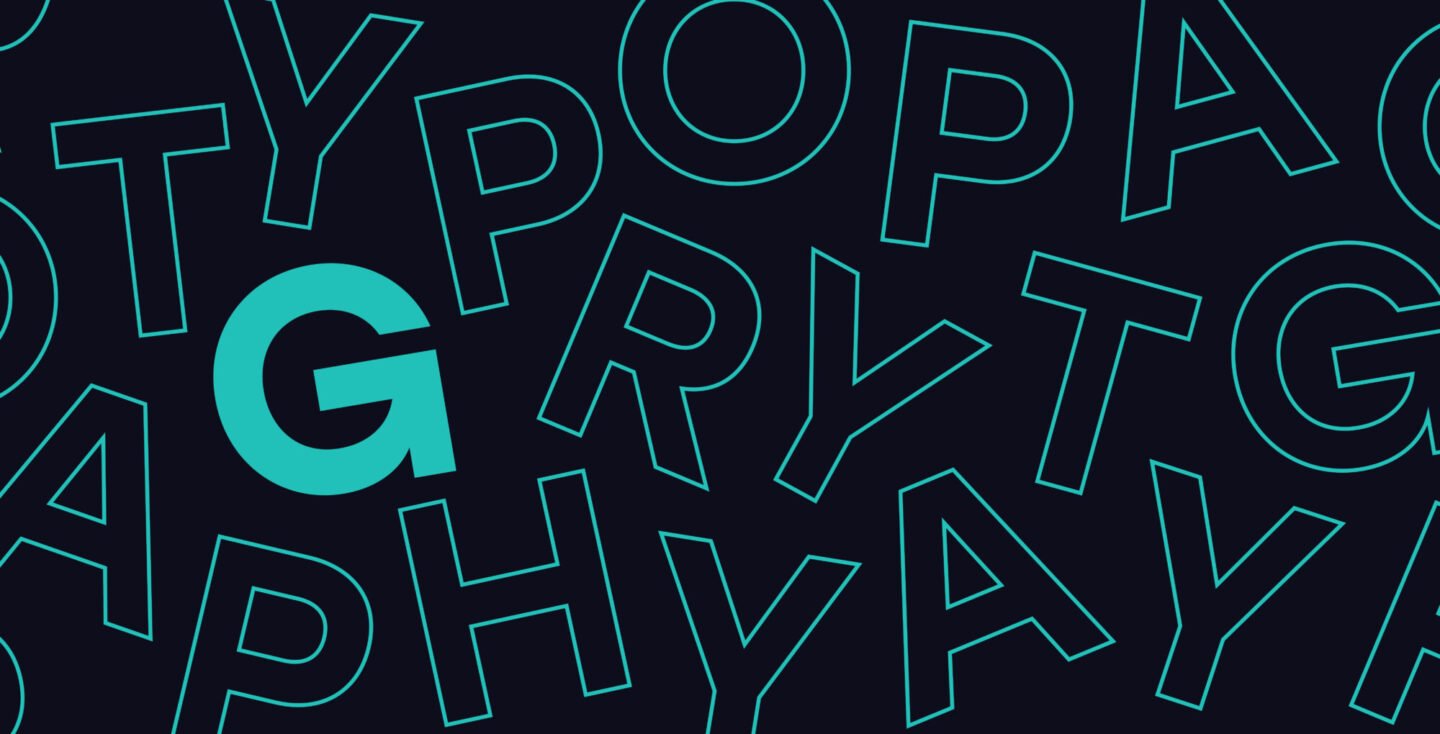
La typographie moderne est l’art de disposer le texte de manière esthétiquement agréable et facile à lire. Dans le passé, la typographie était principalement utilisée pour l’impression de livres et d’autres documents écrits, mais avec l’avènement de la technologie numérique, elle est devenue une partie importante de la conception graphique et de la communication visuelle. Aujourd’hui, le choix d’une police de caractère moderne contribue fortement à l’identité d’un projet visuel.
L’un des principaux principes de la typographie moderne est la hiérarchie. Cela signifie organiser le texte de manière à indiquer clairement l’importance relative de chaque morceau de texte. Par exemple, un titre peut être affiché en police plus grande et plus audacieuse que le texte principal, pour attirer l’attention du lecteur.
Un autre aspect important de la typographie moderne est la lisibilité. Les polices de caractères, ou polices, sont soigneusement choisies pour rendre le texte facile à lire sur différents appareils et à différentes tailles. Par exemple, une police avec une hauteur de x (la distance entre la ligne de base et la ligne moyenne des lettres minuscules) est généralement plus lisible qu’une police avec une faible hauteur de x.
En plus de la hiérarchie et de la lisibilité, la typographie moderne met également l’accent sur le design et l’esthétique. L’utilisation de différentes polices, tailles et styles peut ajouter de l’intérêt visuel à une page et aider à transmettre une humeur ou un ton spécifique. Par exemple, un document officiel peut utiliser une police à empattement, tandis qu’un site Web ludique peut utiliser une police sans empattement plus fantaisiste.
Un des développements les plus intéressants en matière de typographie moderne est l’utilisation de polices personnalisées. Dans le passé, les designers étaient limités à un petit nombre de polices préinstallées, mais maintenant ils peuvent créer leurs propres polices ou utiliser des polices de bibliothèques en ligne. Cela permet une plus grande créativité et flexibilité dans la conception de la typographie. Les polices personnalisées peuvent également être utilisées pour créer une identité de marque unique et différencier une entreprise ou un produit de ses concurrents.